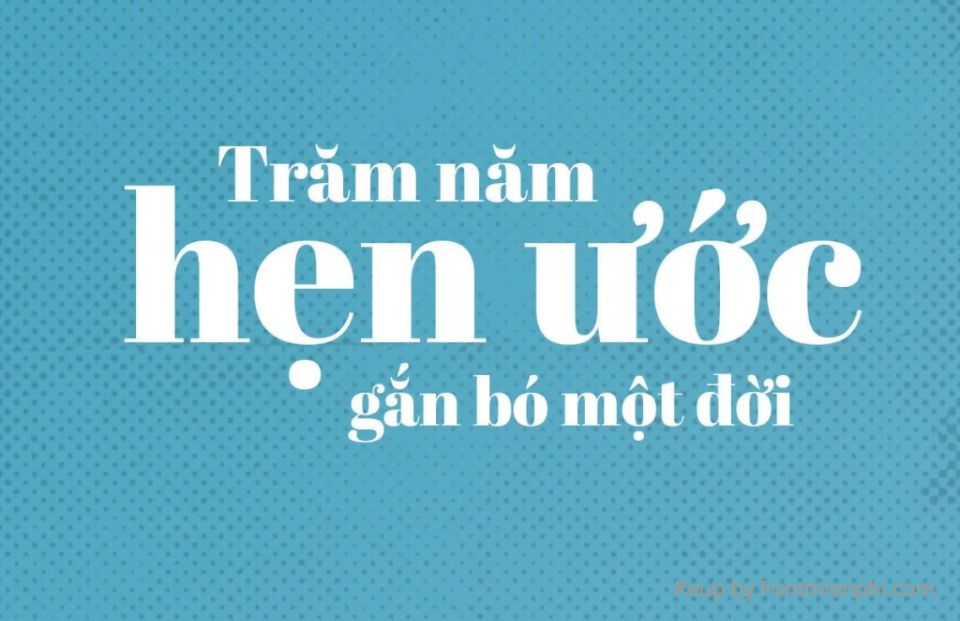
Font VL Abril Fatface Việt Hóa Miễn Phí
Giới Thiệu: Font VL Abril Fatface Việt Hóa Miễn Phí
Nếu bạn đang tìm kiếm một sự phá cách, VL Abril Fatface chính là câu trả lời. Đây là mẫu phông chữ có chân (serif) sở hữu những đường nét dày, to đậm và tràn đầy cá tính. Mang đậm phong cách display (hiển thị) ấn tượng, phông chữ này sinh ra để làm tâm điểm, cực kỳ hoàn hảo cho các thiết kế tiêu đề lớn, banner quảng cáo, poster, thumbnail YouTube hay bất kỳ ấn phẩm branding nào cần tạo ra một sự khẳng định mạnh mẽ.
Đặc biệt, phiên bản được chia sẻ miễn phí trên Fontmienphi.com đã được Việt hoá trọn vẹn. Hệ thống dấu tiếng Việt được chăm chút tỉ mỉ giúp đảm bảo tính thẩm mỹ, đồng bộ cao. Từng ký tự đều được tối ưu để hiển thị sắc nét, rõ ràng, giúp thông điệp của bạn luôn nổi bật trên mọi nền tảng.
🌟 Đặc Điểm Nổi Bật Của Font VL Abril Fatface
• Giao thoa phong cách: Mang trong mình thiết kế serif cổ điển nhưng lại toát lên tinh thần vô cùng hiện đại và thời thượng.
• Thị giác mạnh mẽ: Nét chữ to, dày, tạo độ tương phản cao và cực kỳ thu hút ánh nhìn.
• Tối ưu cho kích thước lớn: Hiển thị đẹp xuất sắc và phô diễn trọn vẹn từng đường nét khi được sử dụng ở các size chữ lớn.
• Thuần Việt 100%: Hỗ trợ đầy đủ bảng mã ký tự và dấu tiếng Việt, không lo lỗi font trong quá trình gõ.
• Đa dụng cho truyền thông: Là lựa chọn “chân ái” cho các thiết kế tiêu đề, poster, banner, logo và các ấn phẩm social media.
🎨 Ứng Dụng Thực Tế
Với sự nổi bật và cá tính riêng biệt, VL Abril Fatface tại Fontmienphi.com đặc biệt phù hợp để biến hóa trong các phong cách thiết kế như:
• Thiết kế editorial cho các tạp chí nghệ thuật, ấn phẩm thời trang.
• Sáng tạo poster quảng cáo phim, sự kiện, ca nhạc.
• Thiết kế banner website, ảnh bìa hoặc bài đăng mạng xã hội.
• Thiết kế thumbnail YouTube cần sự giật tít, thu hút lượt click (CTR cao).
• Xây dựng bộ nhận diện thương hiệu (branding), đặc biệt cho mảng thời trang, F&B.
• Sáng tác các tác phẩm typography nghệ thuật đầy phá cách.